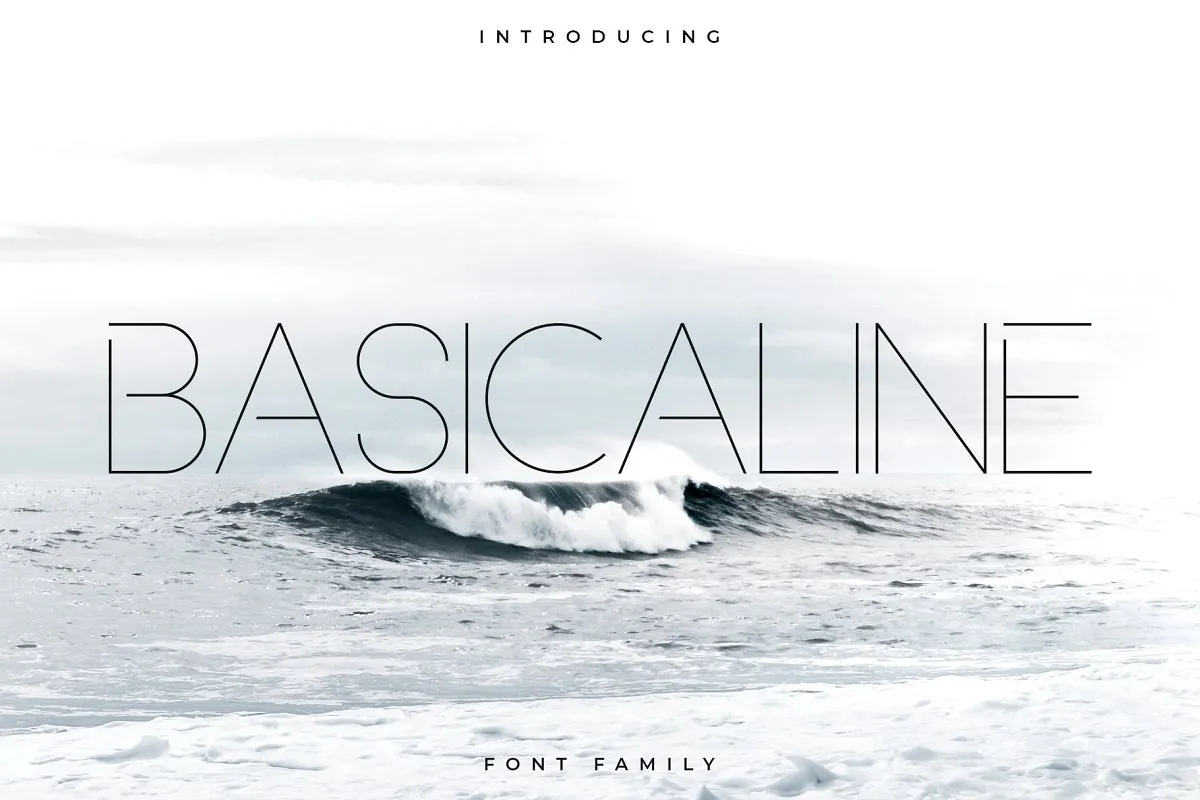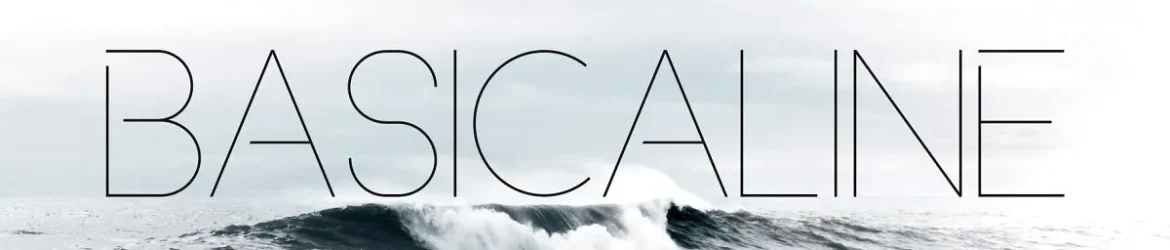
A Basicaline Font Family é uma tipografia sans-serif com contornos arredondados que se destaca por sua simplicidade elegante e clareza. Introduzida para designers de gráficos em busca de uma face moderna e versátil, a fonte apresenta um estilo minimalista que oferece uma aparência impecável para qualquer contexto. Com um design intenso e limpo, a Basicaline é perfeita para criações de marca, logotipos, revistas, vídeos, embalagens de produtos, cabeçalhos de sites e estilização de roupas. Suas linhas claras e sua disposição suave enriquecem qualquer projeto que use essa fonte. Uma escolha versátil para designers modernos atentos ao design gráfico contemporâneo.